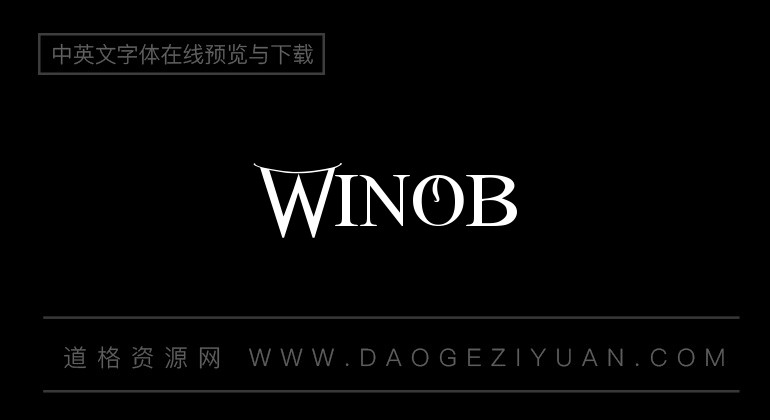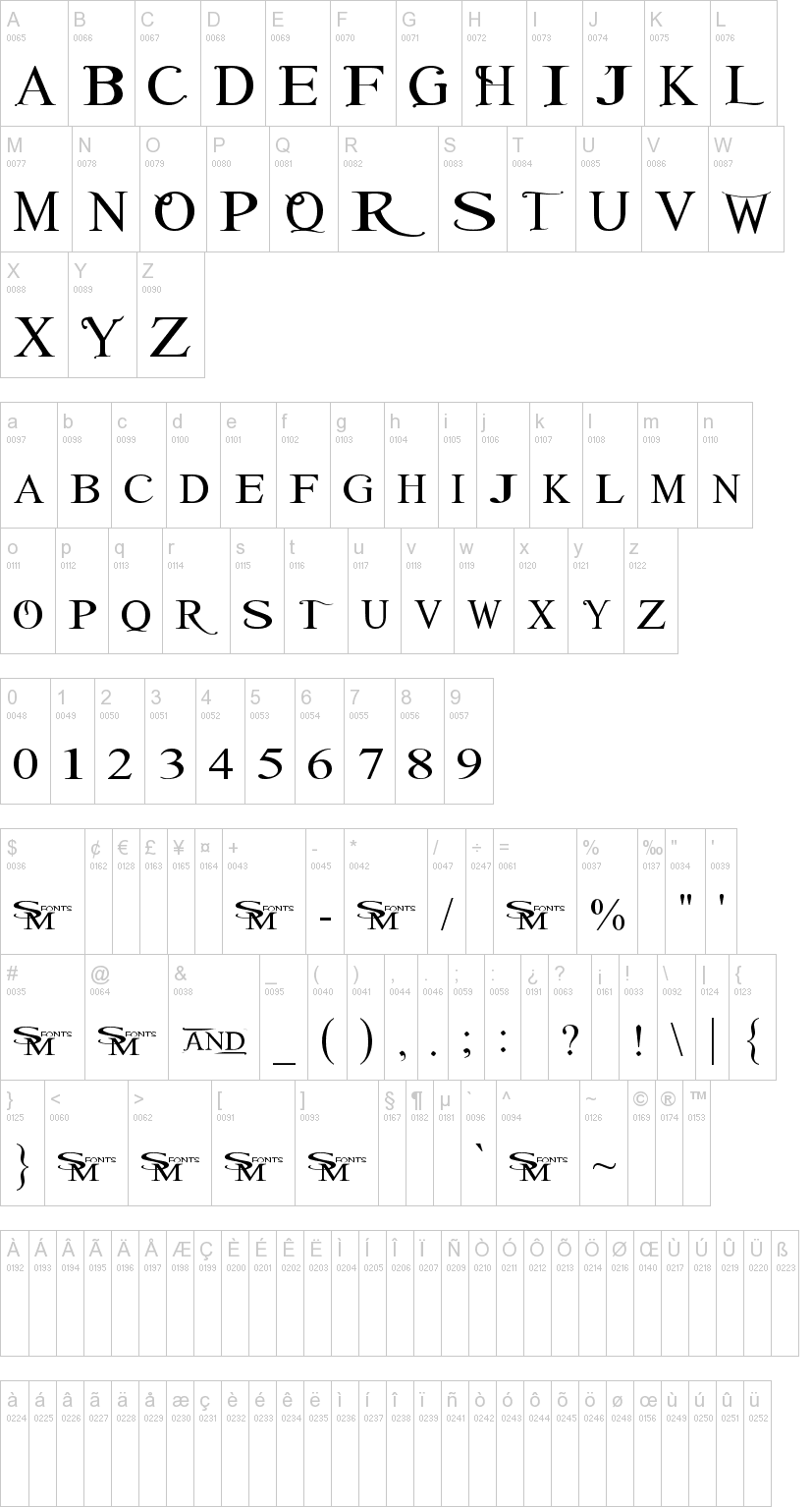
Winob
Winob字体是一种简洁的英文字体,它具有简单的结构和清晰的线条,可以帮助你提升设计的可读性。它适用于所有种类的文本,无论是用于网页标题,文章正文,图形设计,印刷或者其他任何文字介绍。它的特点是拥有清晰的细节和明亮的颜色,可以让你的文字介绍看起来更加精致和清晰。
Winob是一款非常不错的手写艺术字体,具有很好的视觉感,适合于文化类的宣传设计、商业类品牌的广告和产品包装设计以及个性化文字排版等较多场景。